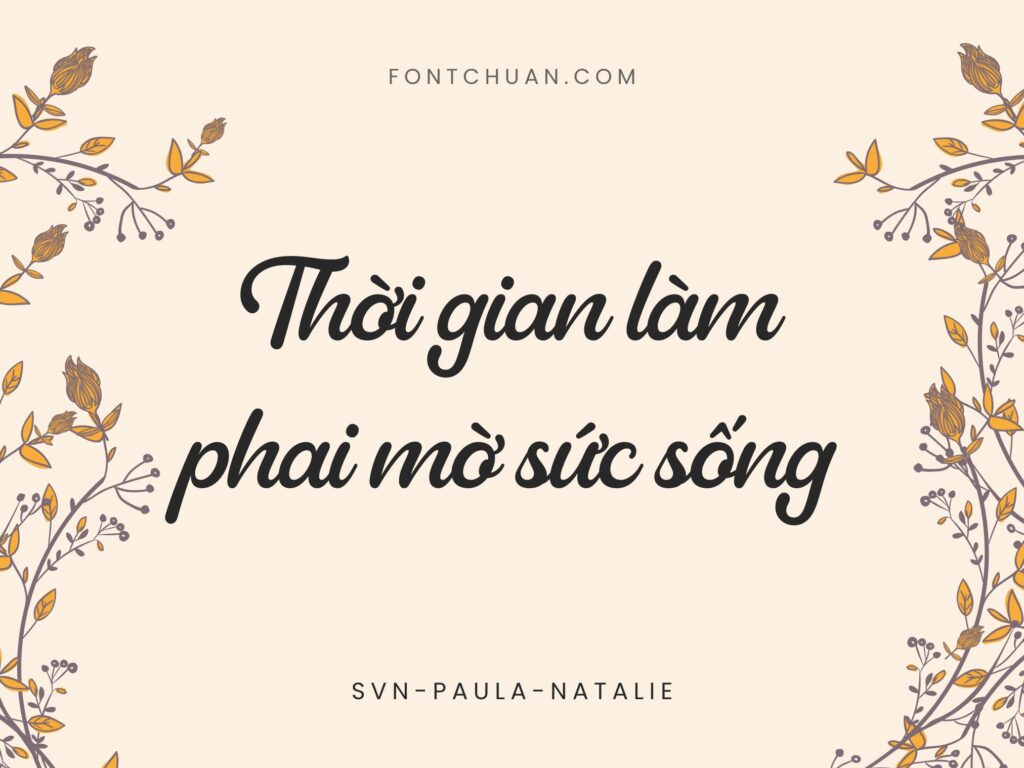
Font SVN Paula Natalie Việt Hóa
Tác giả Font: Akhmad Reza Fauzi
Font SVN Paula Natalie là phiên bản Việt hóa của kiểu chữ Paula Natalie, được thực hiện bởi STYLEno.1 Fonts. Paula Natalie là một kiểu chữ script đáng yêu và vui nhộn, được thiết kế bởi Akhmad Reza Fauzi và phát hành bởi Grezline Studio. Font này được tạo ra để mang đến sự tươi vui cho các tiêu đề và dự án logotype. Paula Natalie bao gồm đầy đủ các ký tự chữ hoa, chữ thường, chữ số và dấu câu, hỗ trợ đa ngôn ngữ. Font này phù hợp cho nhiều mục đích sử dụng khác nhau như thiết kế logo, bìa sách, áp phích, trích dẫn, bao bì sản phẩm, hàng hóa, truyền thông xã hội và nhiều hơn nữa.
SVN Paula Natalie lý tưởng cho các dự án thiết kế yêu cầu sự vui tươi và thân thiện, như thiết kế logo, tiêu đề, bao bì sản phẩm và các ấn phẩm truyền thông. Các ngành nghề như giáo dục, ẩm thực và thiệp cưới có thể tận dụng font này để tạo điểm nhấn trong thiết kế. Ngoài ra, font cũng thích hợp cho các sự kiện như Sinh nhật, Valentine, Tết và các lễ hội khác.